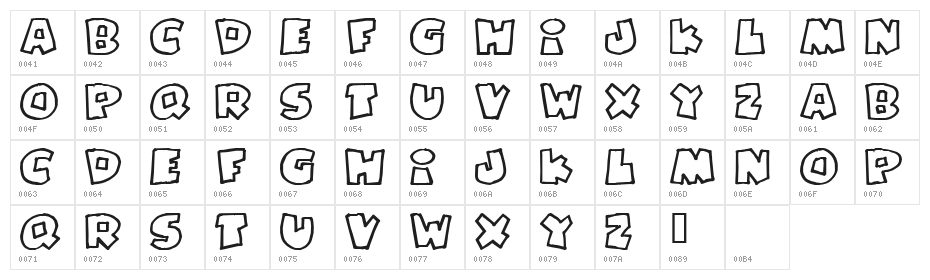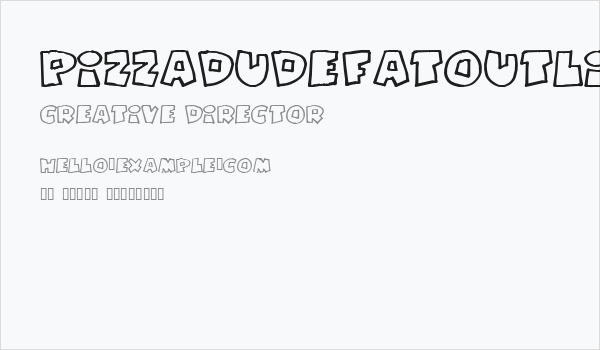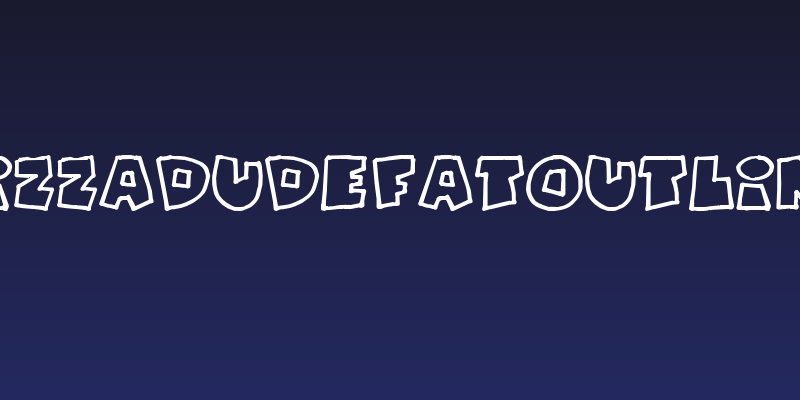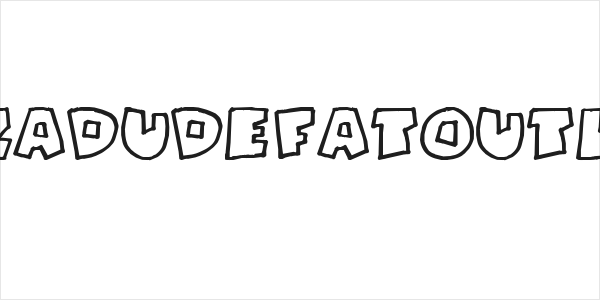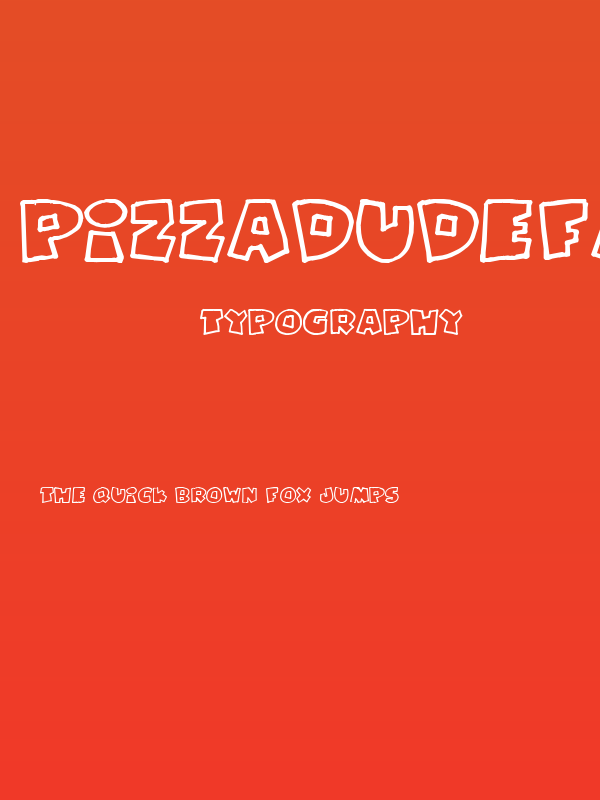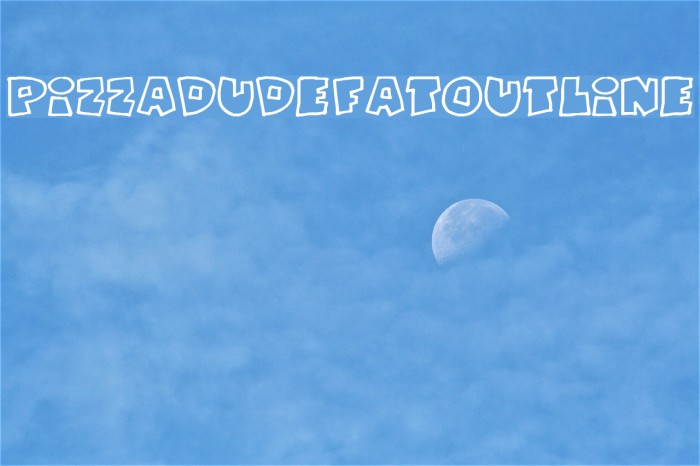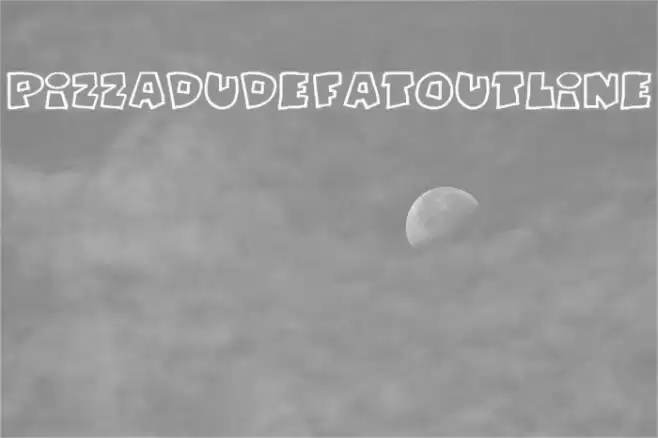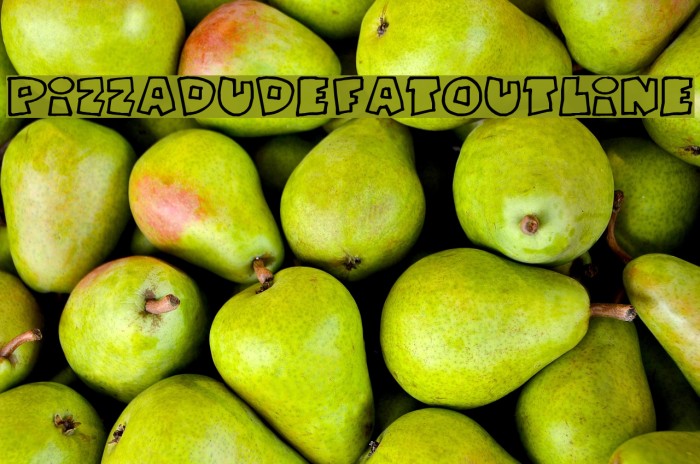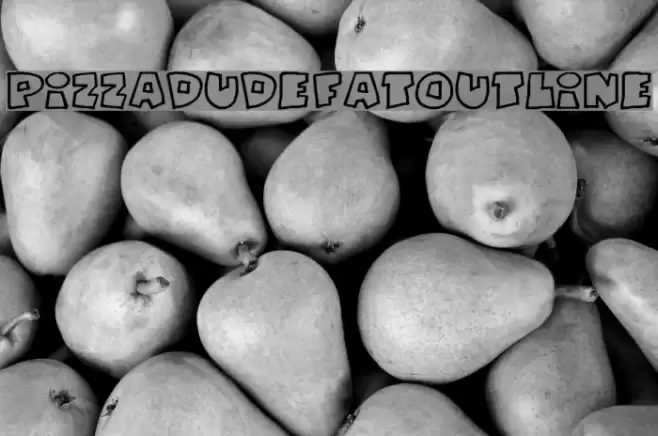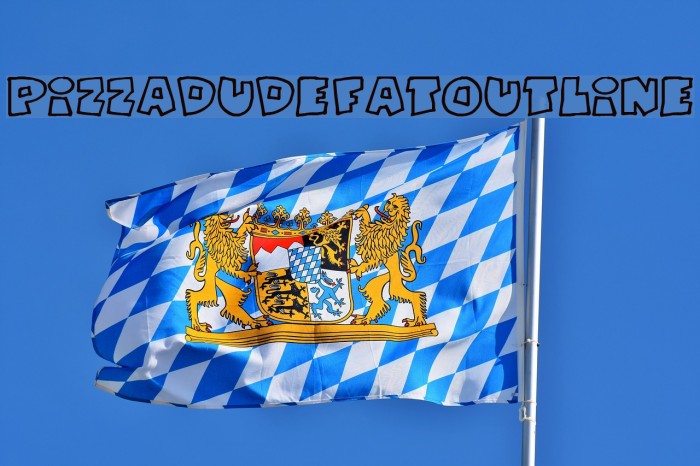
PizzaDudeFatOutline Font
✎ Outline
| Gesamtstil | Playful, Cartoonish, Whimsical |
| Vorgeschlagene Projekte | Ideal for children's books, comic strips, playful branding, and eye-catching posters. |